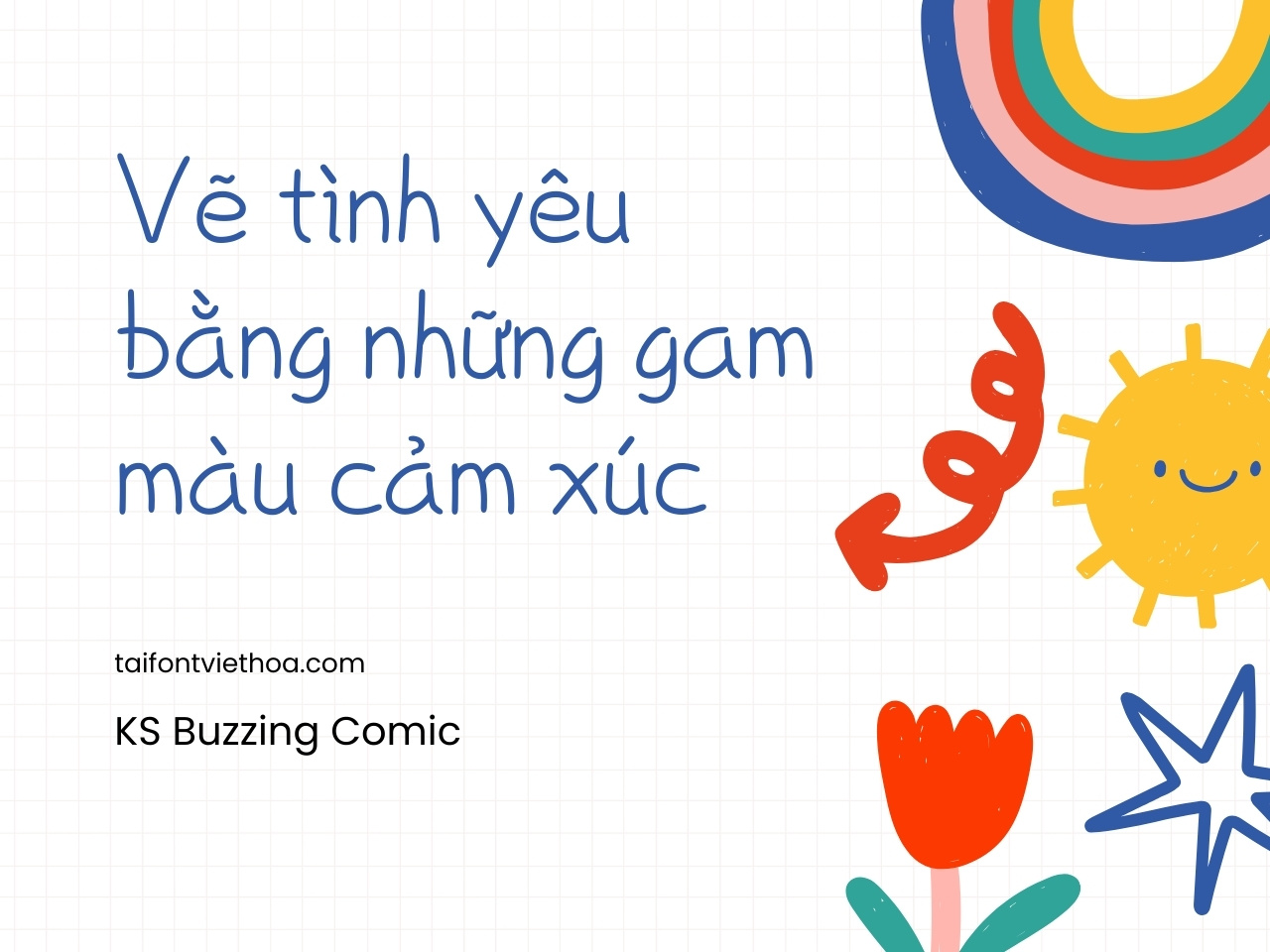
Font việt hóa Ks Buzzing Comic
Giới thiệu font Ks Buzzing Comic – Phong cách viết tay hoạt hình sinh động
Ks Buzzing Comic là một kiểu font viết tay (handwritten) mang phong cách hoạt hình ngộ nghĩnh và dễ thương, được Việt hóa bởi Kiên Sinh. Font được lấy cảm hứng từ truyện tranh thiếu nhi, bảng chữ cái tự nhiên của trẻ nhỏ, và tinh thần vui vẻ, tự do trong sáng tạo. Với thiết kế nét tròn, nhảy múa và hơi bất quy tắc có chủ đích, font này tạo cảm giác vui nhộn và đáng yêu từ cái nhìn đầu tiên. Phiên bản Việt hóa hỗ trợ đầy đủ tiếng Việt và hơn 80 ngôn ngữ khác. Ks Buzzing Comic đã được taifontviethoa.com chọn lọc và chia sẻ như một lựa chọn hoàn hảo cho những ai đang tìm kiếm một bộ font dễ thương, sáng tạo, thích hợp cho các thiết kế dành cho thiếu nhi, lễ hội và các nội dung gần gũi, thân thiện.
Đặc điểm hoạt hình và ứng dụng đa dạng của Ks Buzzing Comic
Font có cấu trúc chữ bo tròn, ngẫu hứng, kết hợp với khoảng cách chữ rộng rãi, tạo nên cảm giác nhẹ nhàng, dễ đọc và tràn đầy năng lượng tích cực. Rất phù hợp cho các thiết kế như banner sinh nhật, thiệp mời lễ hội, bao bì bánh kẹo, sản phẩm trẻ em, đồ chơi giáo dục, thiết kế trang trí trường học, lớp học online hoặc thương hiệu đồ ăn vặt, trà sữa. Font cũng phù hợp với các ngành như ẩm thực, ảnh cưới theo phong cách trẻ trung, giáo dục thiếu nhi, truyền thông thương hiệu vui nhộn hoặc các chiến dịch marketing mùa lễ hội. Đặc biệt lý tưởng cho các sự kiện như sinh nhật, trung thu, lễ hội hoặc ngày Nhà giáo.